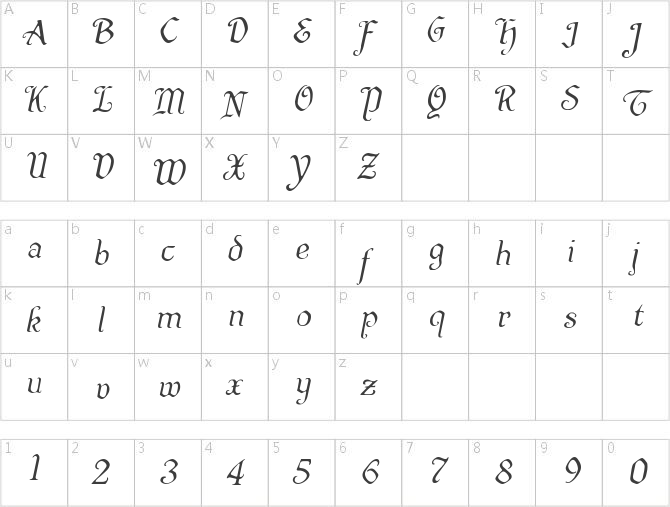
Quill Sword Light Italic
Quill Sword Light Italic介紹
Quill Sword Light Italic字體字庫是一款讓人賞心悅目、百看不厭的英文字體,適合各類廣告和產品包裝設計應用,字體大小0.1MB,格式為ttf字體,上傳用戶是順新廣告?,作者/版權方為未知